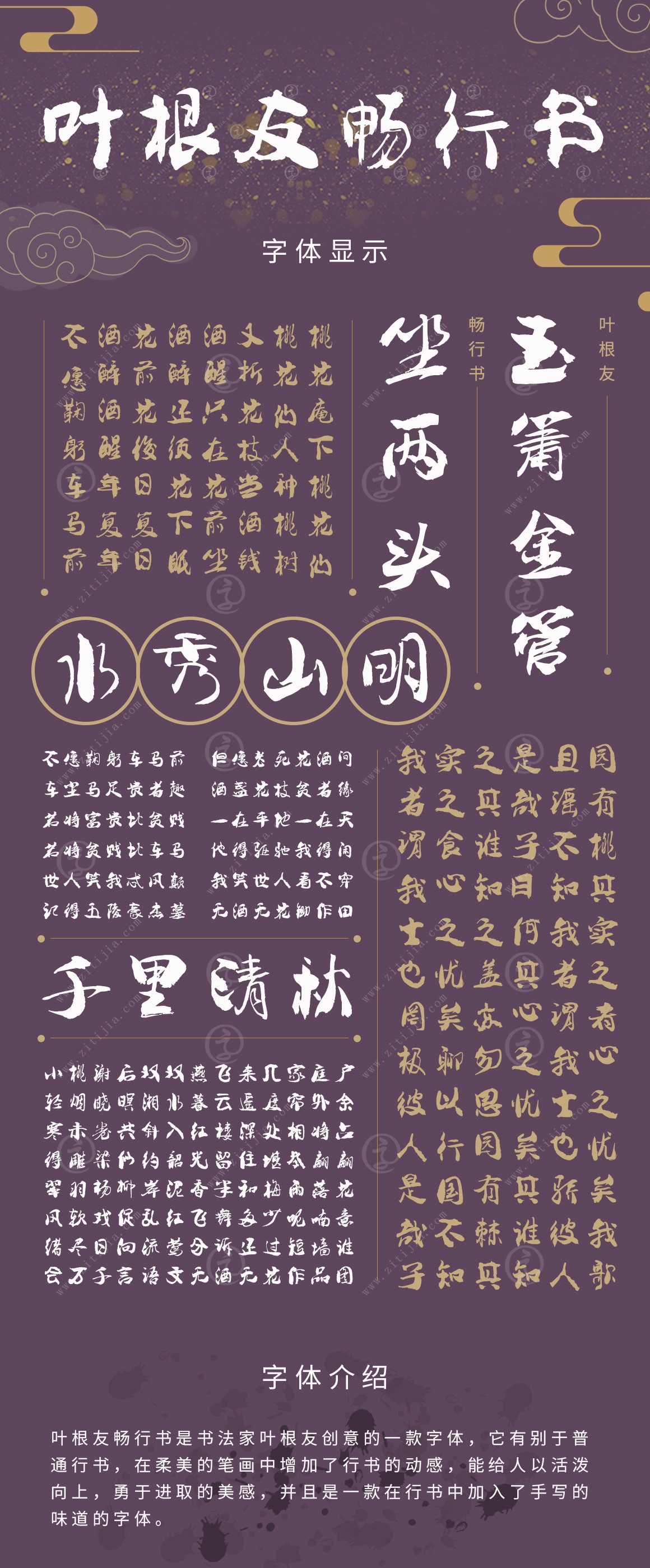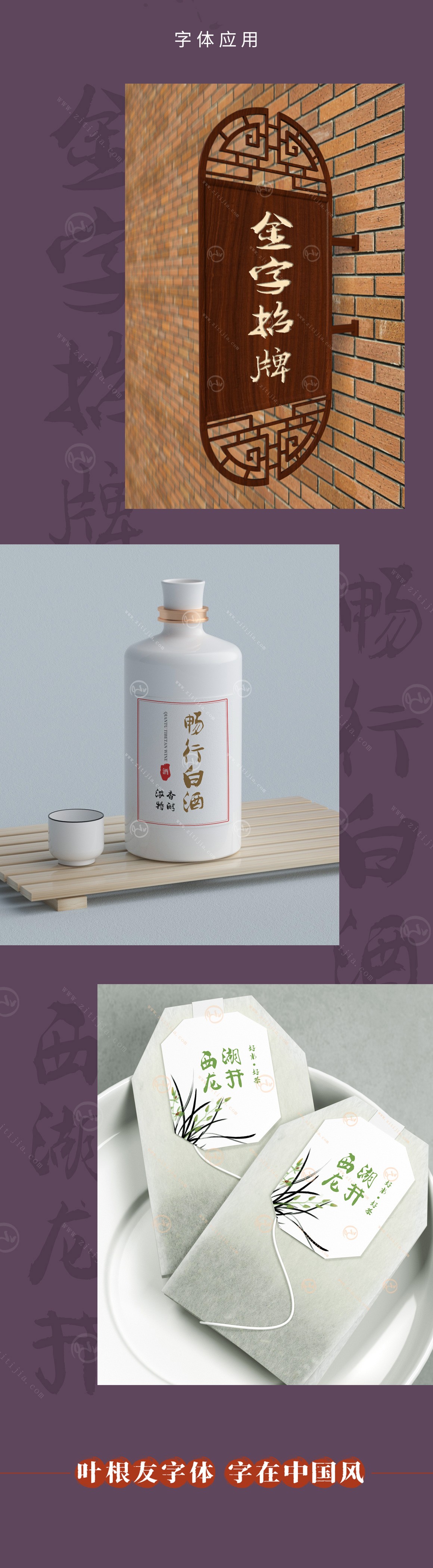
葉根友暢行書
字體作者:葉根友
創(chuàng)作年代:2015年
字體介紹
葉根友暢行書是一款2015年最新創(chuàng)作的行書字體,這款字體是葉根友行書繁的簡體風(fēng)格版本,從2008年到2015年,歷時七年的變化和書法風(fēng)格路線的創(chuàng)新,葉根友的書風(fēng)也引起了一定的變化,在字面上,書寫的更加流暢和筆勢上筆走龍蛇之輕車駕馭,在標(biāo)題應(yīng)用、廣告標(biāo)語等不錯的應(yīng)用選擇。